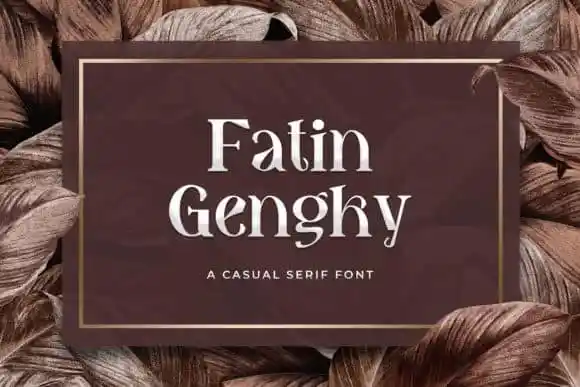
Introduzimos a Fatin Gengky Serif Font, uma tipografia serif com caracteres fortes e robustos. Ideal para uso tanto no texto de destaque como na escrita longa ou na criação de logotipos, essa fonte pode dar um toque clássico às suas criações. É perfeita para quem procura uma fonte serif autêntica e bem estruturada, que se encaixa em uma vasta gama de projetos criativos. Desenvolvida pelo sartstudio na plataforma 99designs, a Fatin Gengky Serif Font oferece um design único e facilmente compatível com diversos estilos gráficos. Seja para criar posters impactantes ou logotipos clássicos, essa fonte será uma excelente escolha. Sua sofisticação se combina perfeitamente com seu caráter robusto e forte, tornando-a um recurso indispensável no seu arsenal de criações visuais. Adicione a Fatin Gengky Serif Font à sua coleção de fonts favoritas e observe como ela transforma seus projetos em verdadeiros marcos.